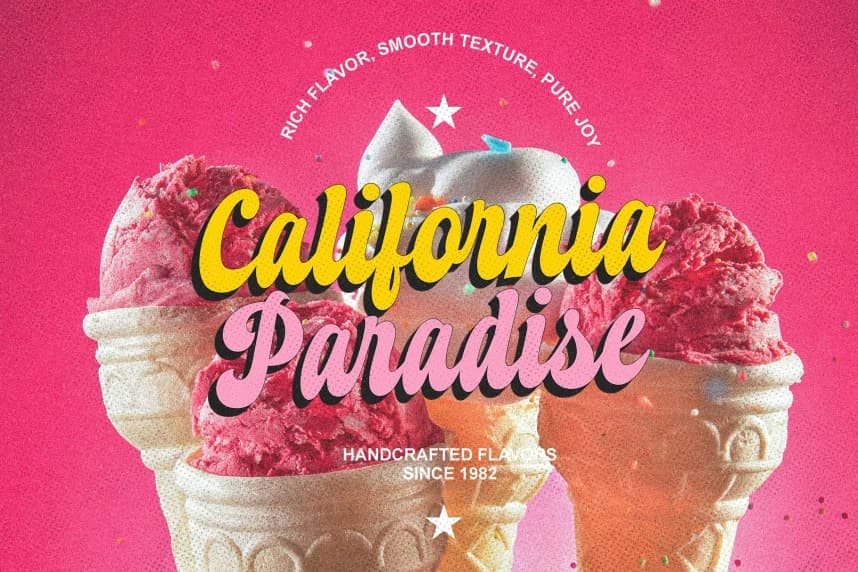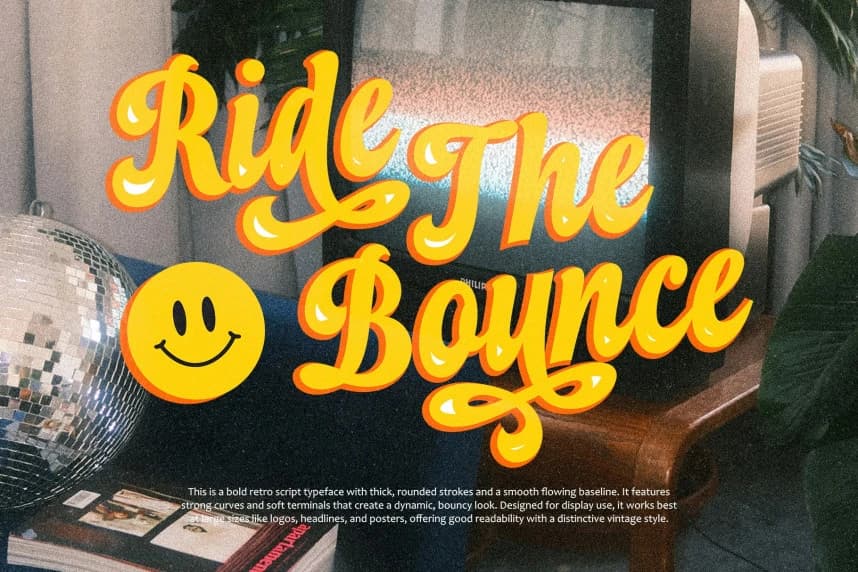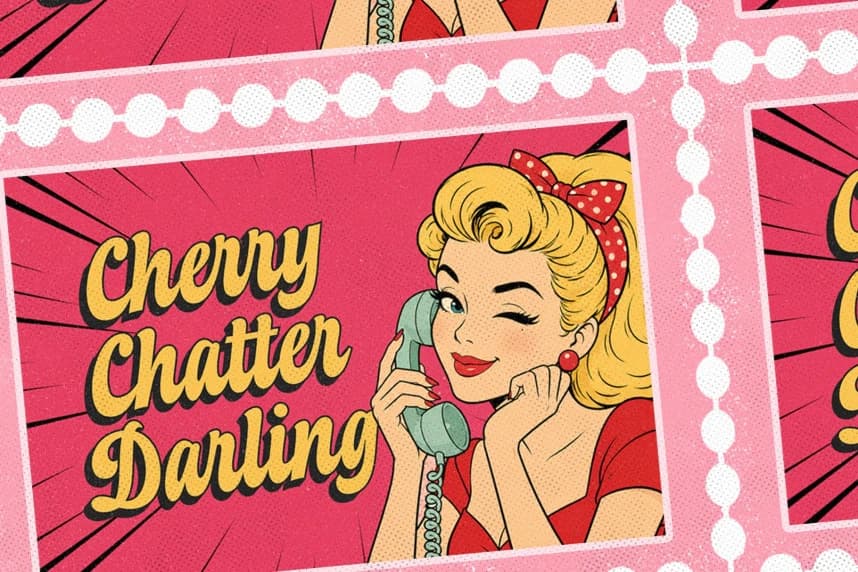
Duckin Script Font, retro stilinde bir script fontu olup kalın karakterler, dinamik akış ve eğlenceli harf biçimleriyle dikkat çeker. Klasik vintage estetiğini eğlenceli groovy dokunuşuyla bir araya getirir ve güçlü bir kişilik ile görsel etki yaratmayı hedefleyen tasarımlar için mükemmeldir.
Duckin Script Font, kalın karakterler, dinamik akış ve oyuncu harf biçimleriyle öne çıkan retro tarzı bir el yazısı fontudur. Klasik vintage estetiğini eğlenceli bir groovy dokunuşuyla birleştirir ve bu da güçlü bir kişilik ve görsel etkiyle öne çıkmayı hedefleyen tasarımlar için mükemmel hale getirir.